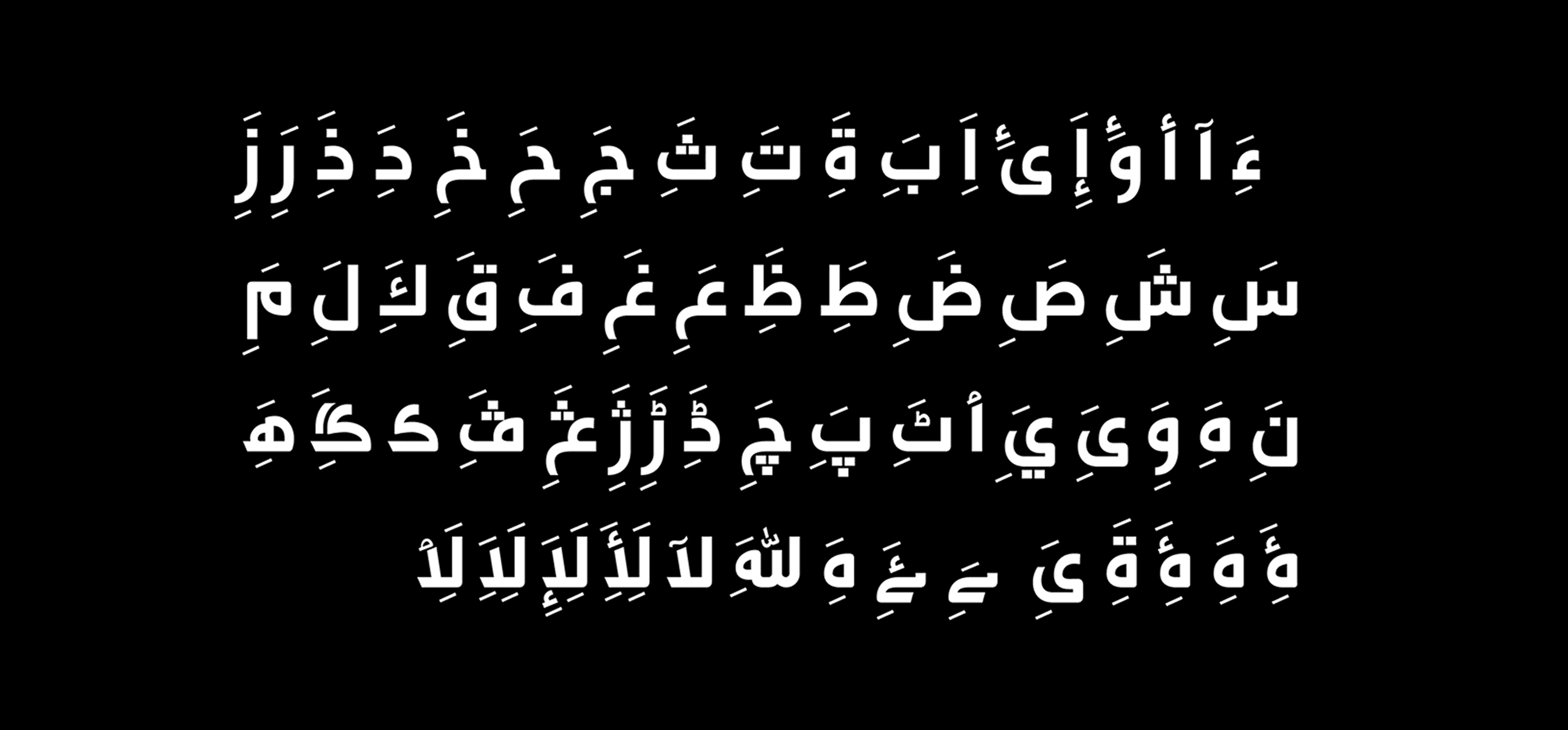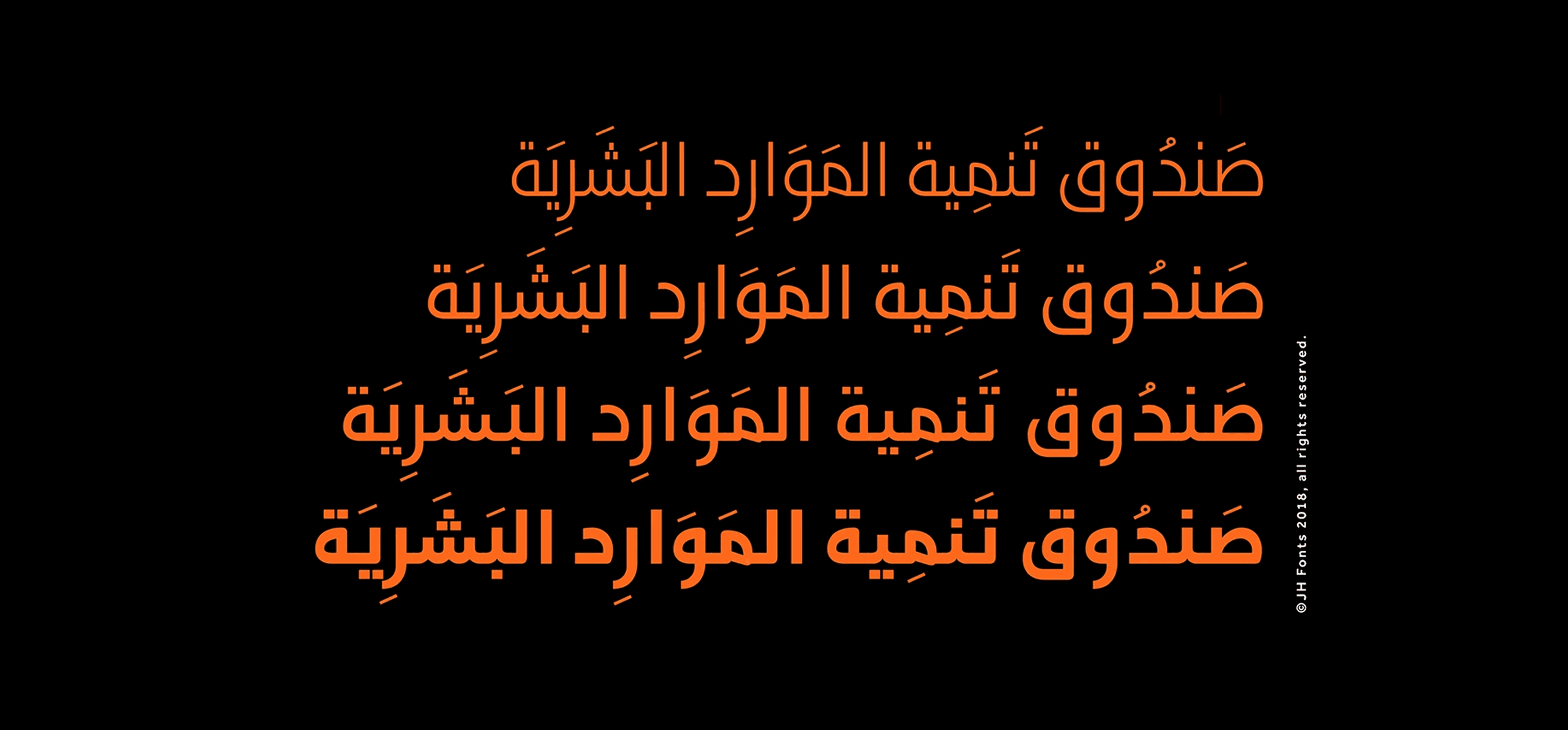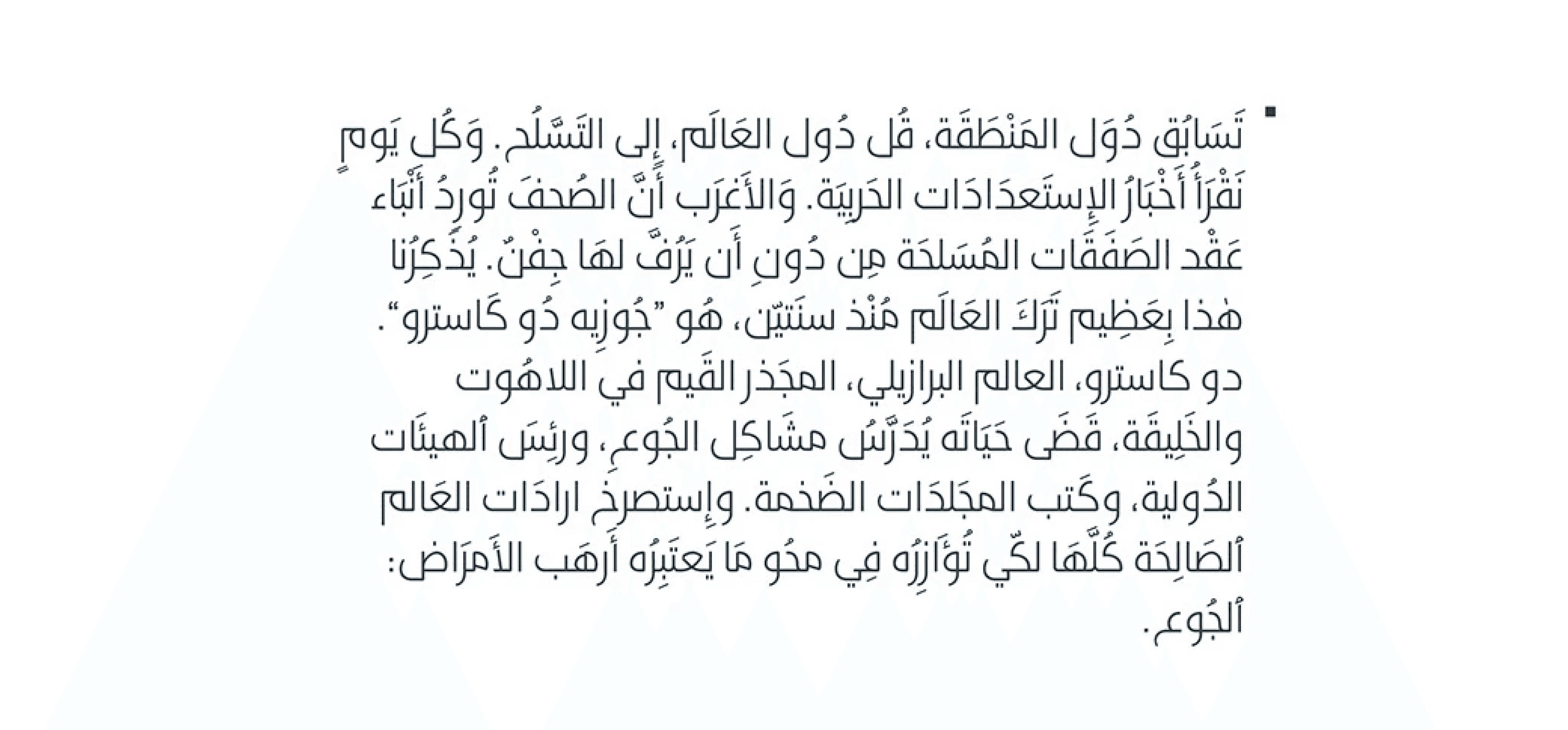
الخط JH Hala هو خط عصري الطابع، تم تصميمه بناءً على أسلوب الكوفي وتصنيف اللاتيني الإنساني الخالي من الزوائد (Humanist Sans Serif).
يُعد مناسبًا للهويات البصرية، العلامات التجارية، واللافتات...